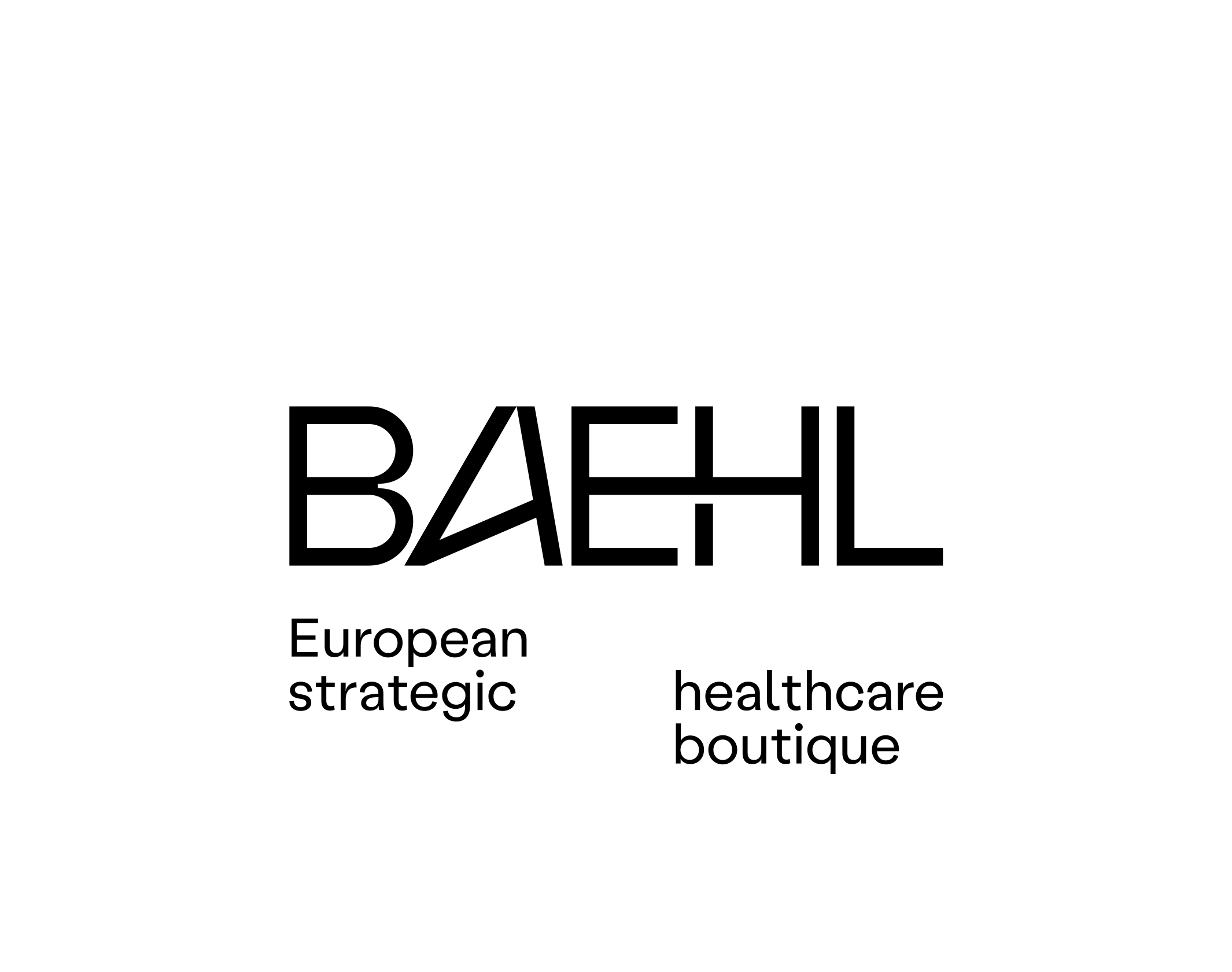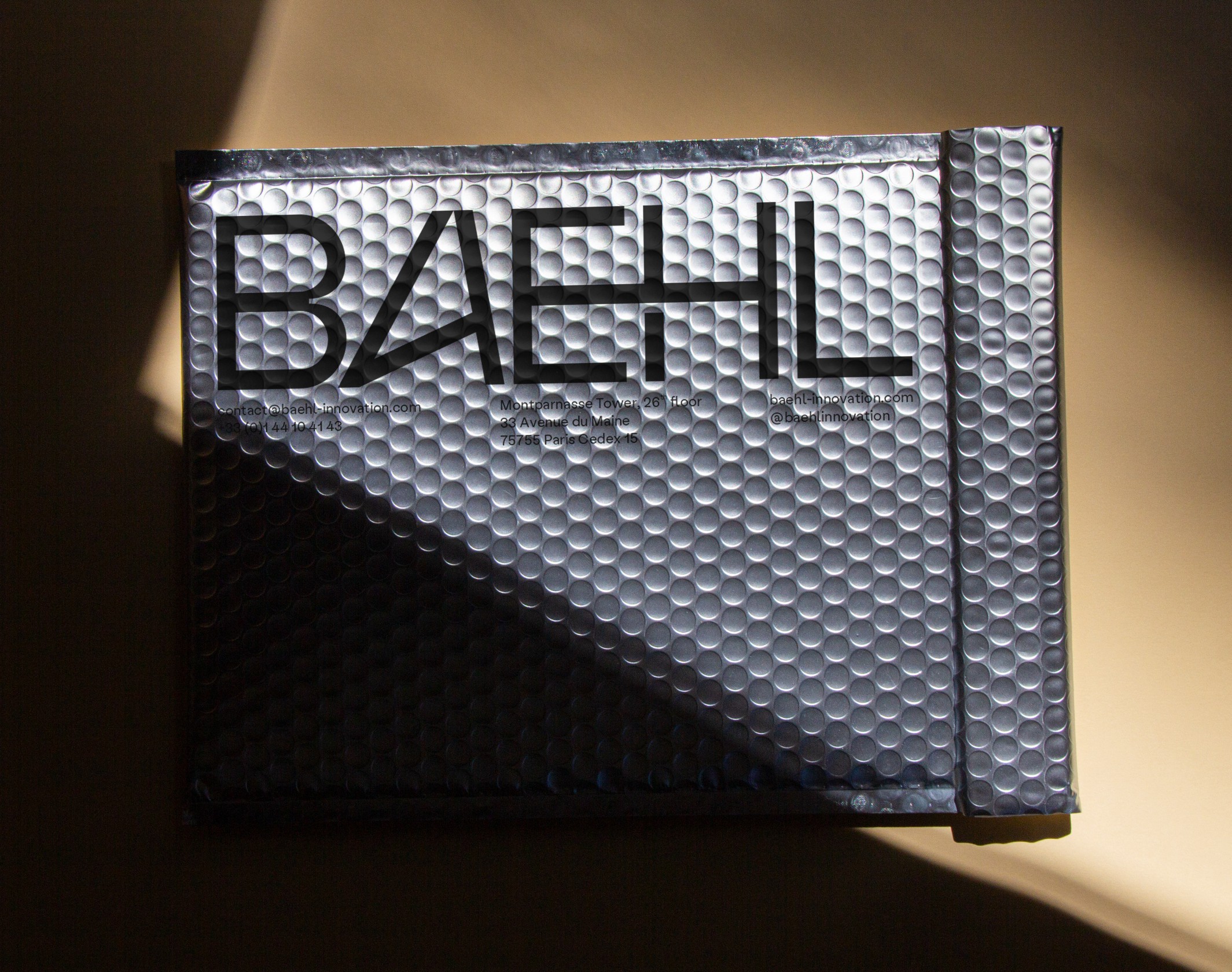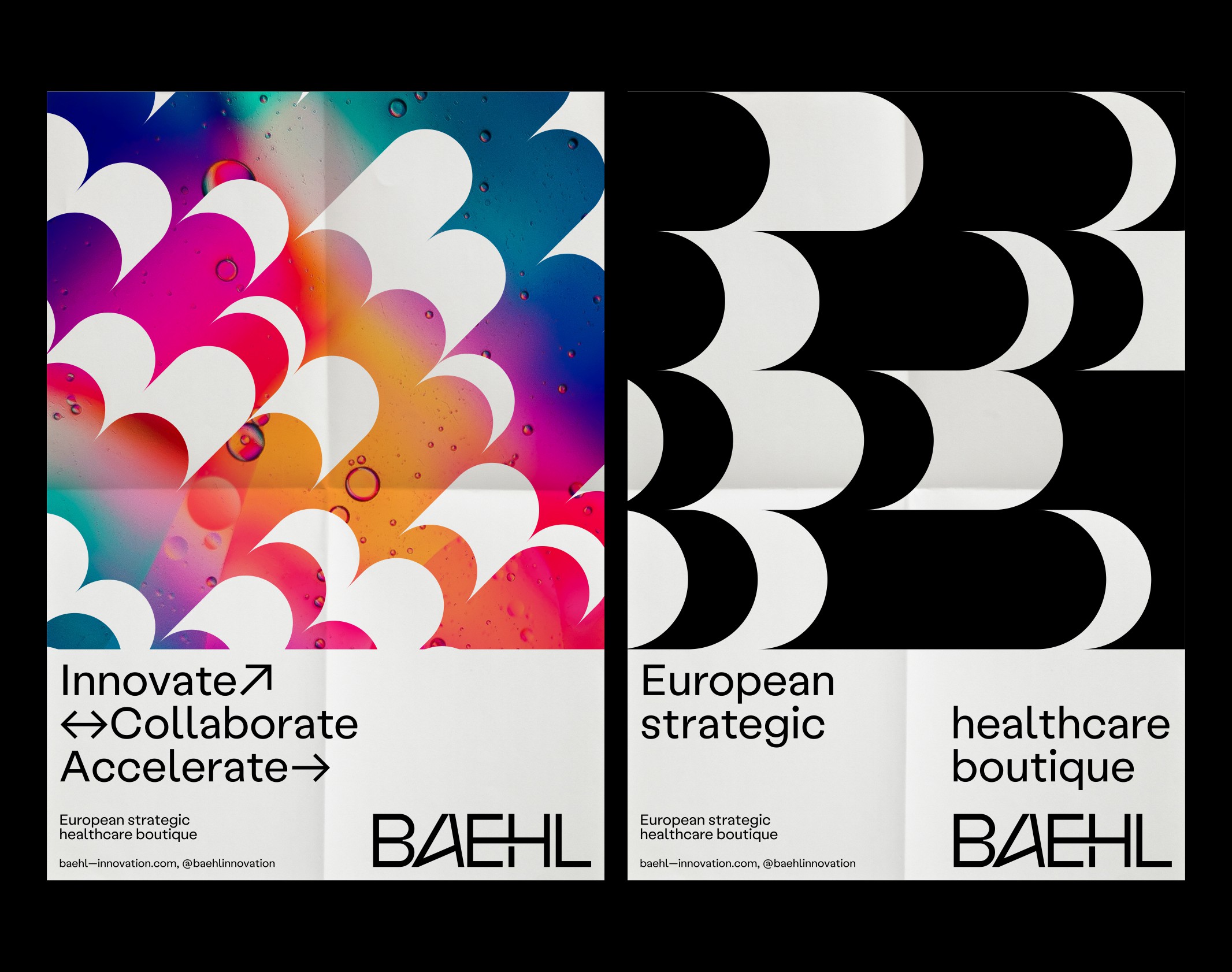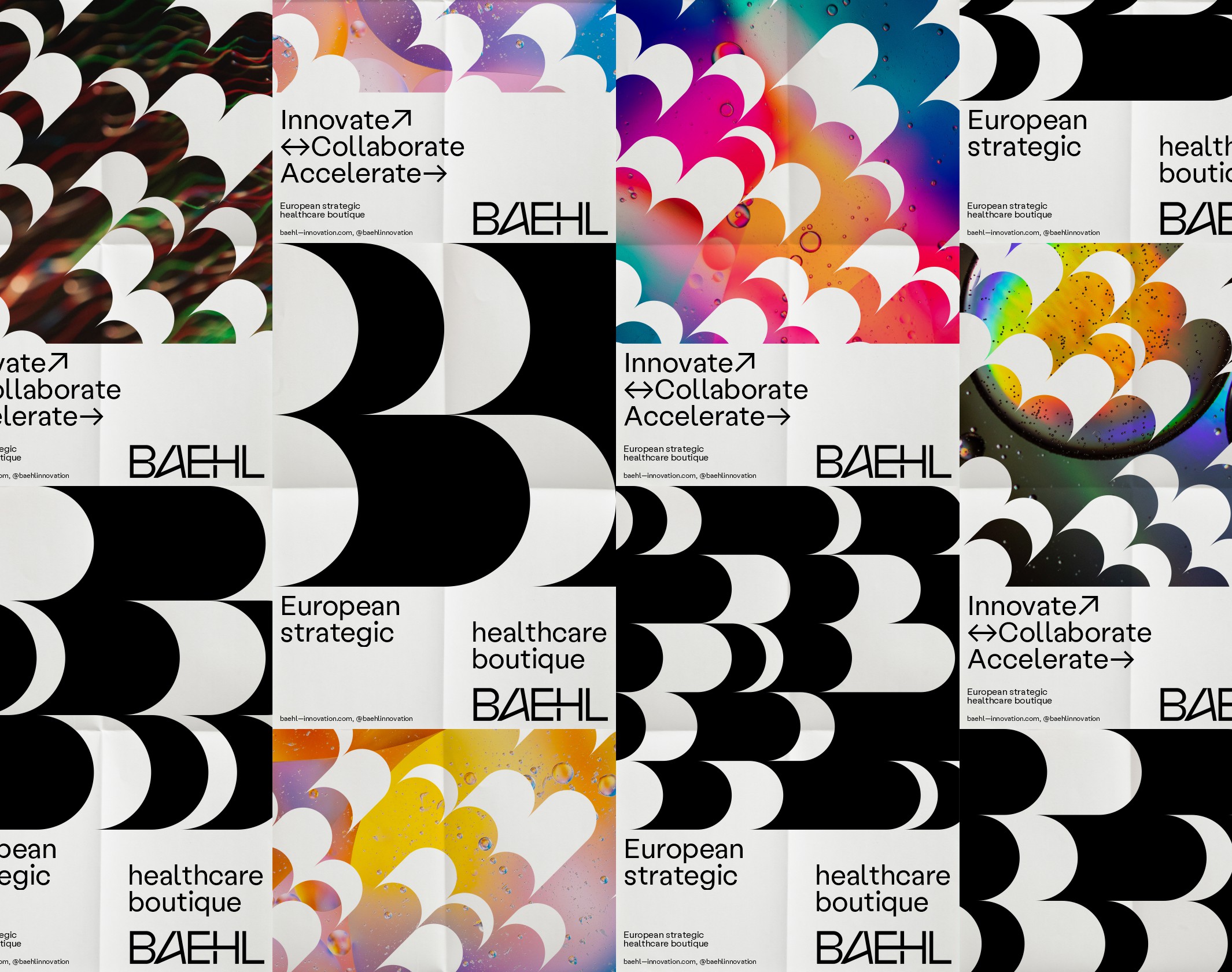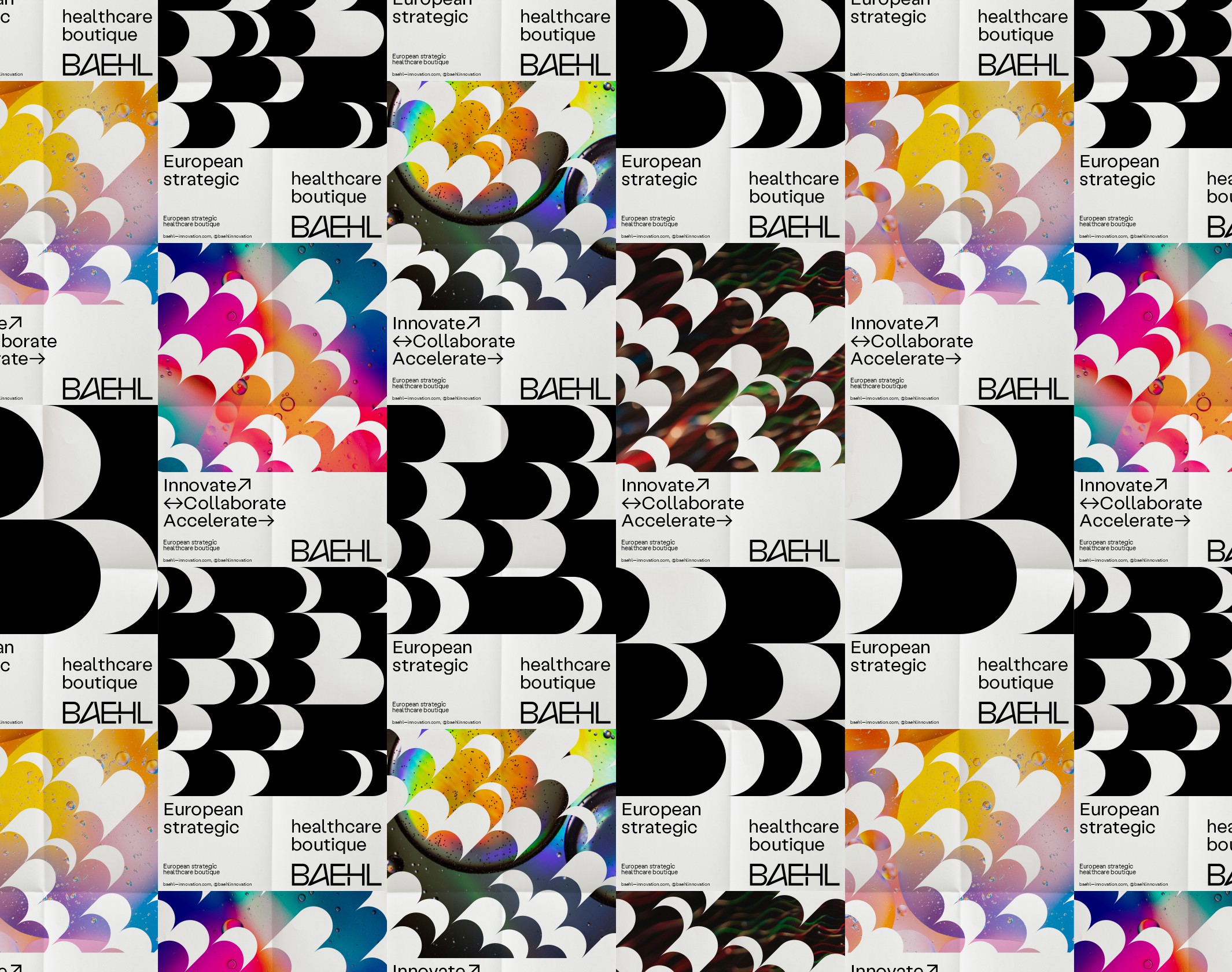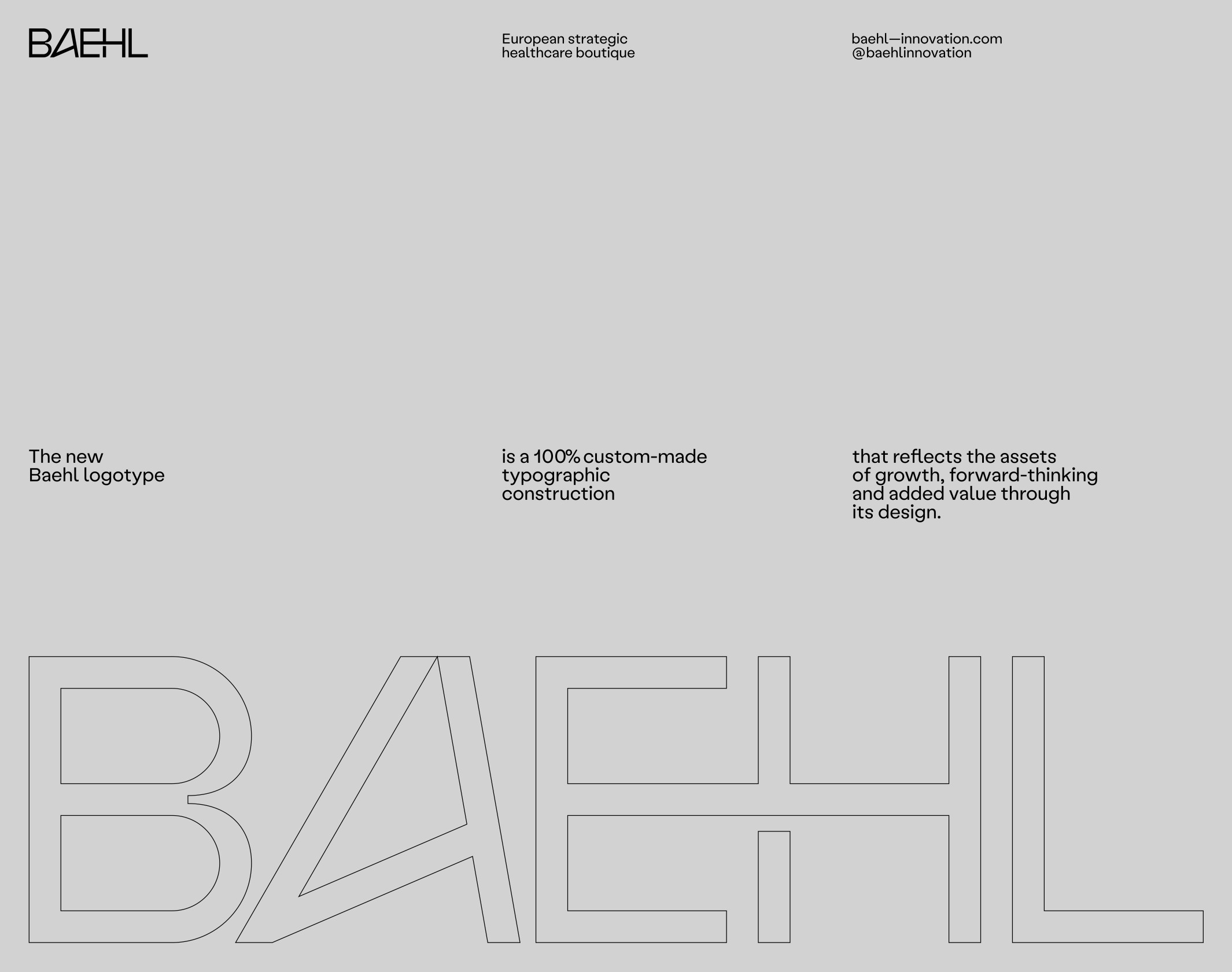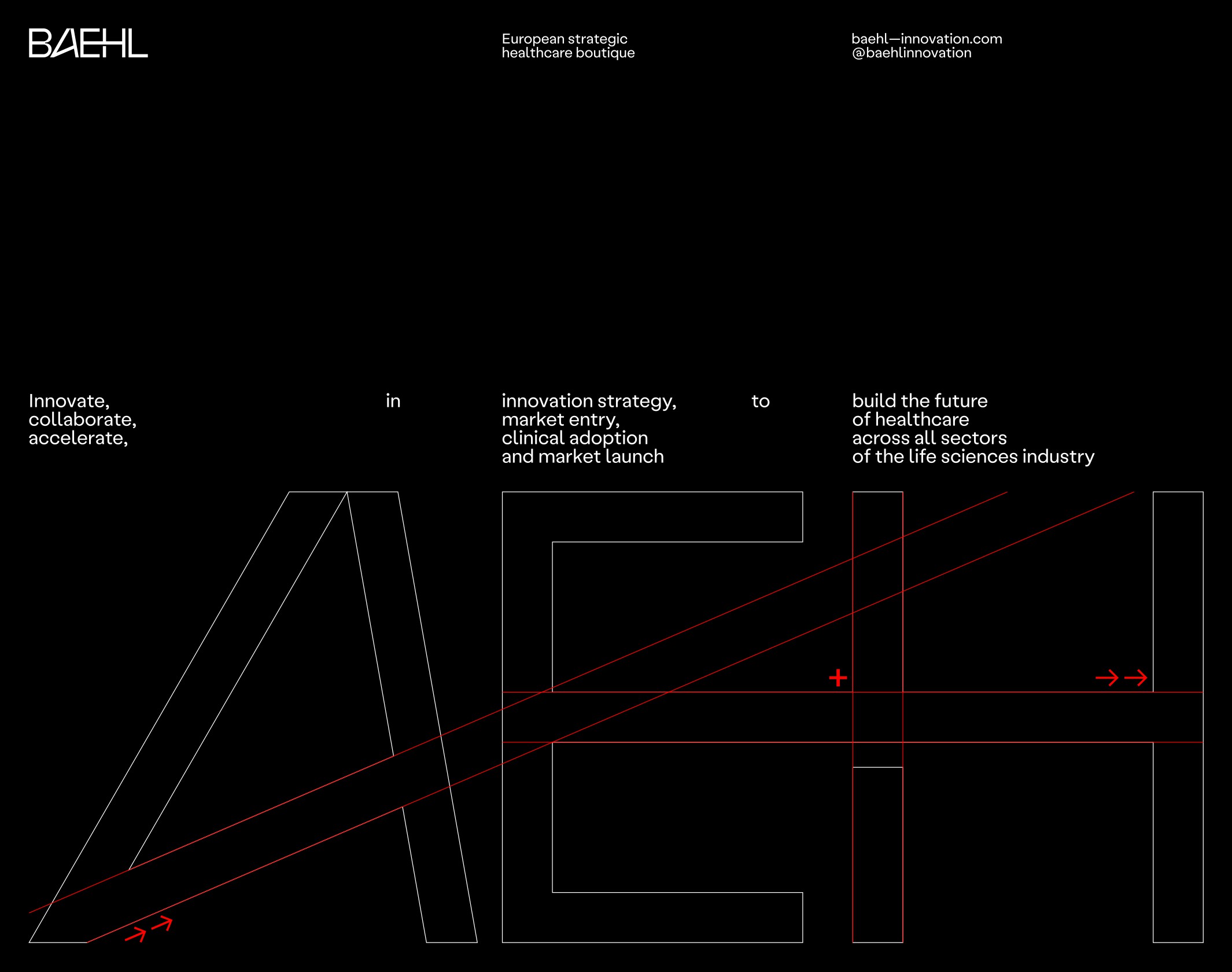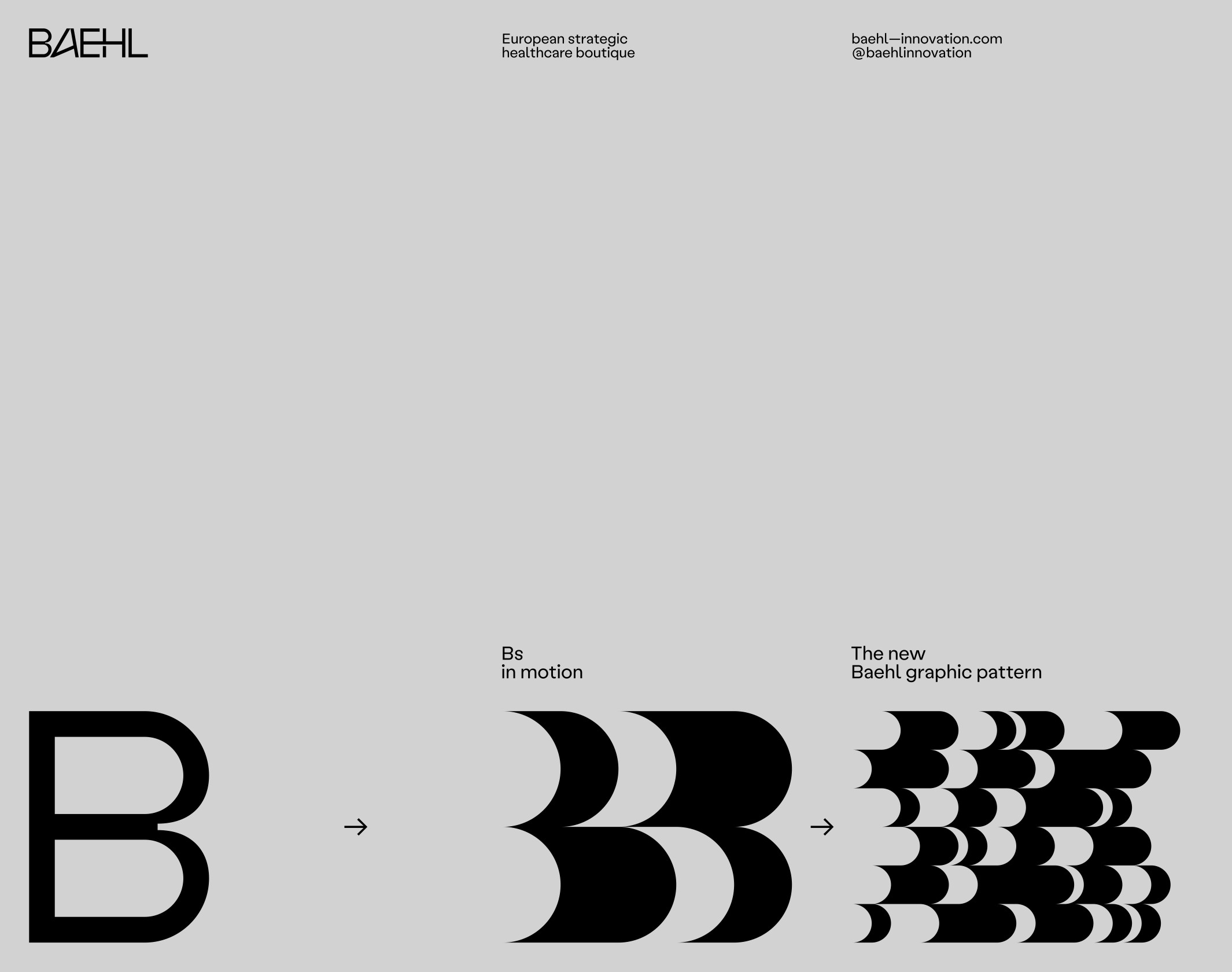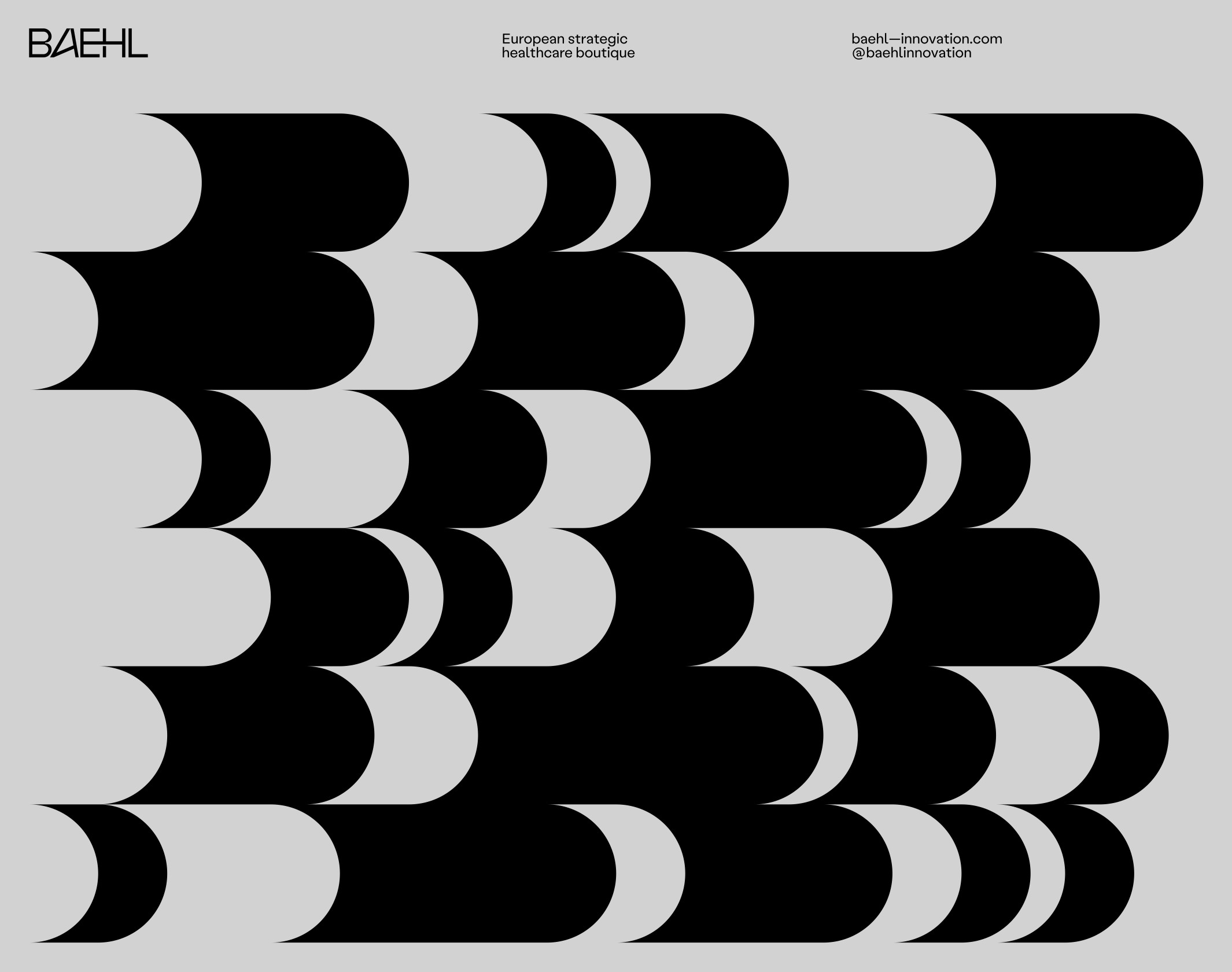
Baehl
Brand Brothers a redéfini l'identité graphique de Baehl avec un typogramme innovant symbolisant la croissance et l'avenir des produits de santé.
Baehl se définit comme boutique de conseil en stratégie fournissant des services en matière d’innovation, de mise sur le marché, d’adoption clinique et de lancement produit dans le secteur pharmaceutique et santé. Basée à Paris mais opérant dans de nombreux pays, elle travaille sur les problématiques les plus avancées liées à l’innovation pour la santé, propose des services intégrés et couvre le cycle de vie complet d’un produit ou d’une entreprise. Baehl est une équipe d’innovateurs, de stratèges, de scientifiques, de médecins et « d’explorateurs » chevronnés qui, ensemble, contribuent à construire l’avenir des produits de santé dans tous les secteurs de l’industrie des sciences de la vie.
Brand Brothers a été chargé de redéfinit l’identité graphique de l’entreprise. Nous avons opté pour un typogramme fin mais structuré, conçu pour l’occasion, dont les lignes évoquent avec subtilité une dynamique de croissance et de projection vers l’avant. Sur la base des courbes du B, nous avons développé un motif génératif, utilisé en monochrome noir ou couplé à des textures expérimentales rappelant l’univers de la recherche. Cette texture riche et organique est complétée par un graphisme simple et structuré, basé sur le caractère Labil Grotesk (Kometa).